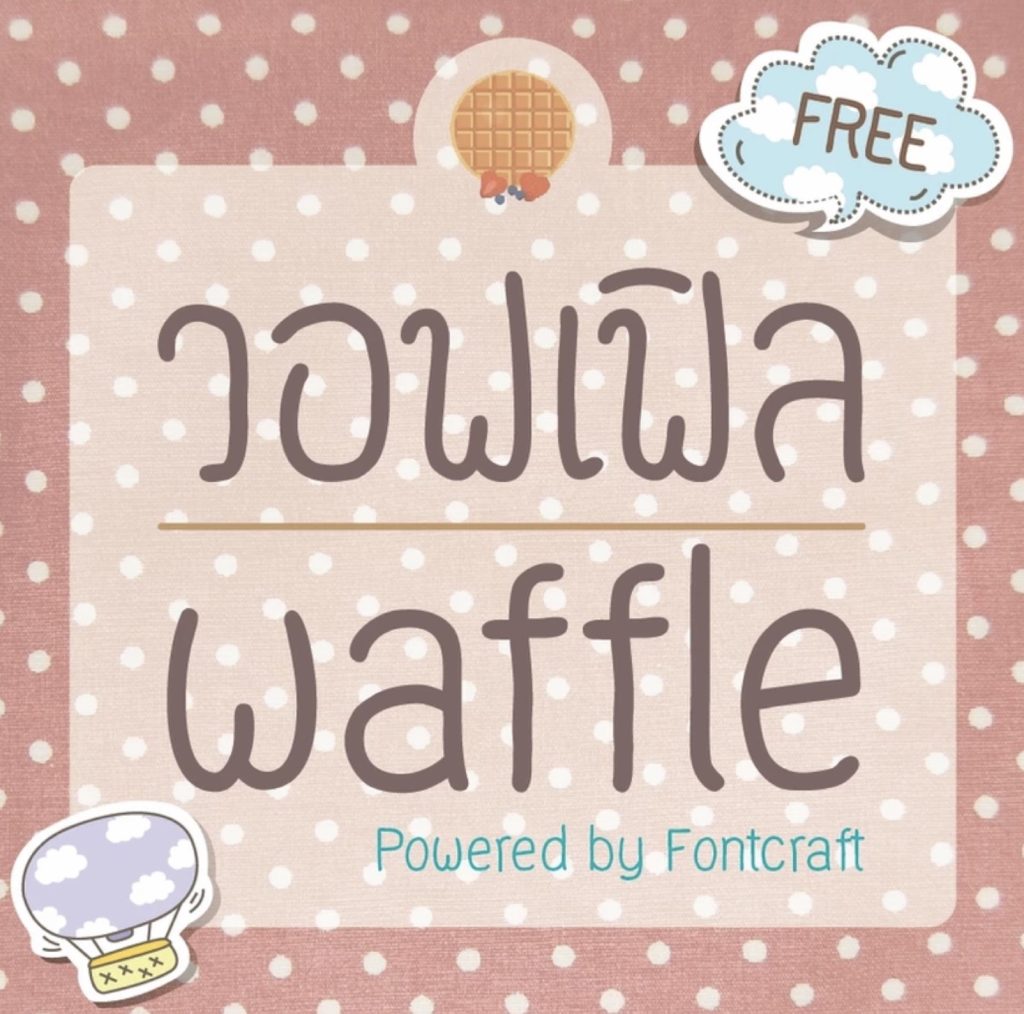
ฟอนต์เป็นส่วนหนึ่งที่ช่วยให้ผลงานนำเสนอหรืออาร์ตเวิร์คนั้นมีความสวยงาม สำหรับใครที่กำลังหาฟอนต์ไทยน่ารัก ๆ ไปตกแต่งผลงานส่วนบุคคล ทีมงานได้รวบรวมฟอนต์จาก Fontcraft หรือเรียกชื่อย่อว่า FC มาแนะนำให้ดาวน์โหลดไปใช้งานกันค่ะ
รวม 8 ฟอนต์ไทย คัดมาแล้วว่าน่ารัก ตกแต่งสวย จาก Fontcraft ดาวน์โหลดฟรี
1. เอฟซี มาร์ชเมลโล่ (FC Marshmallow)
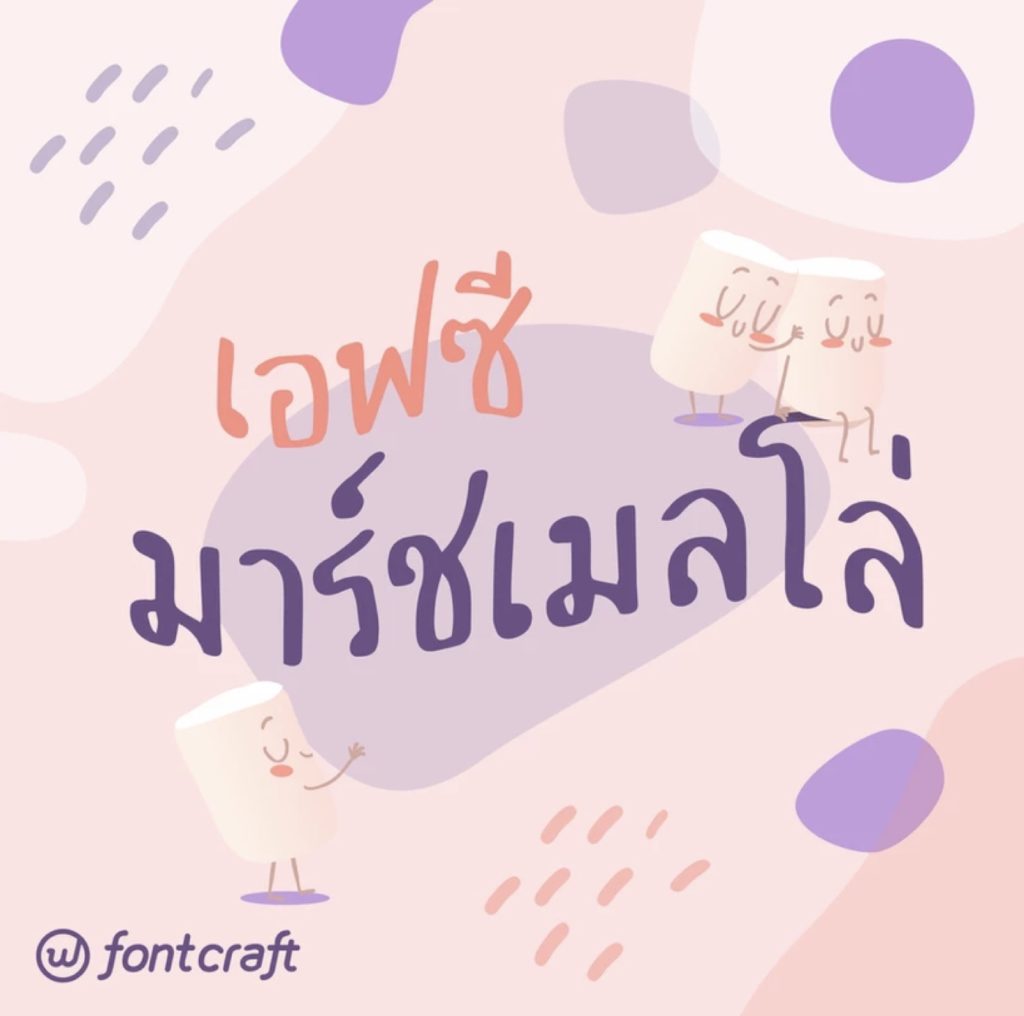
2. เอฟซี มอเตอร์เวย์ (FC Motorway)
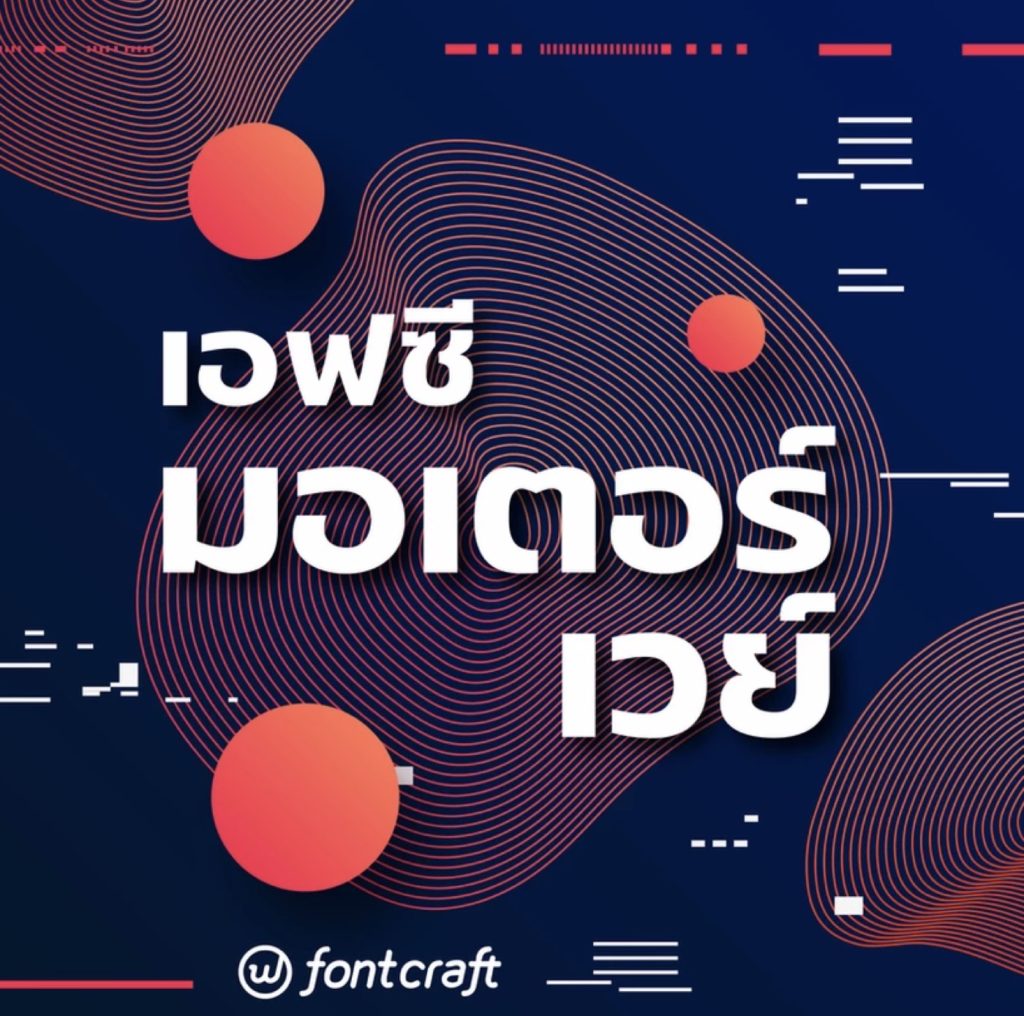
3. เอฟซี มัฟฟิน (FC Muffin)
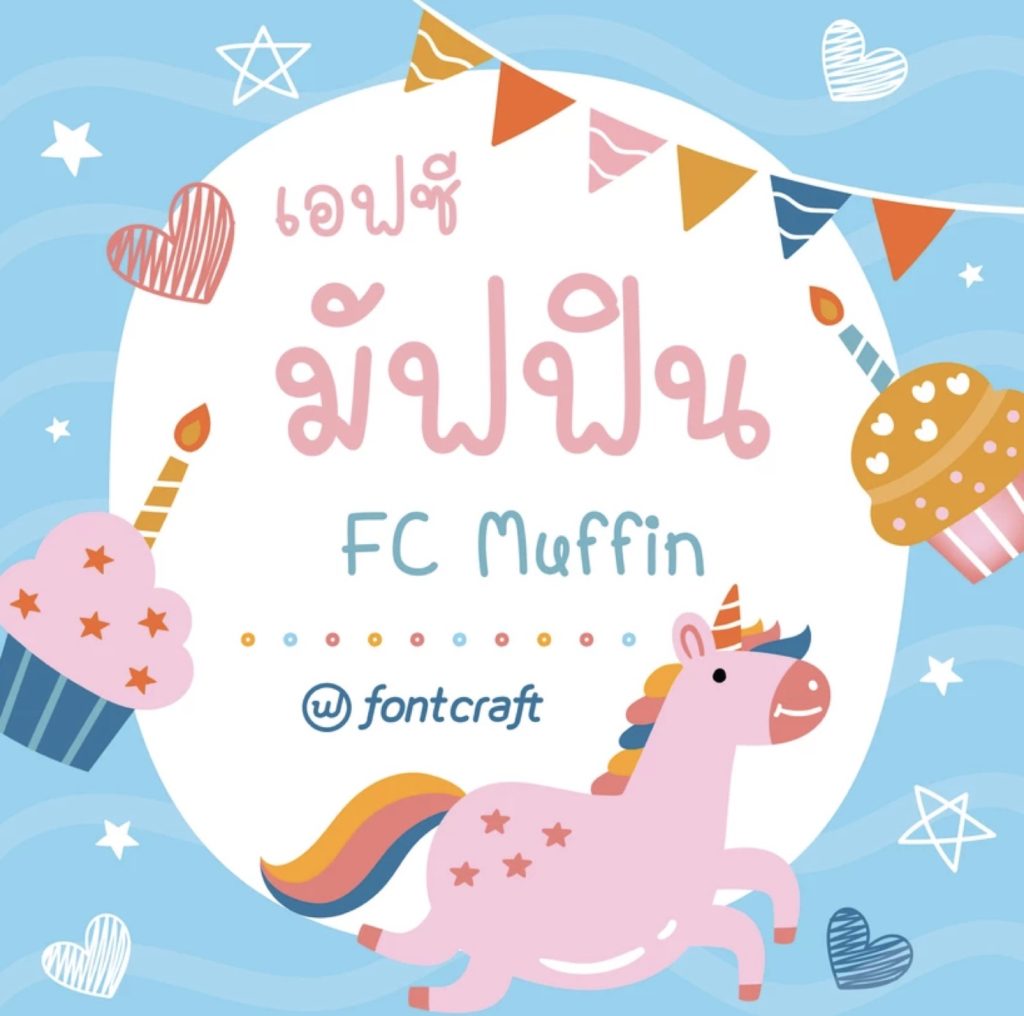
4. เอฟซี โฮม (FC Home)
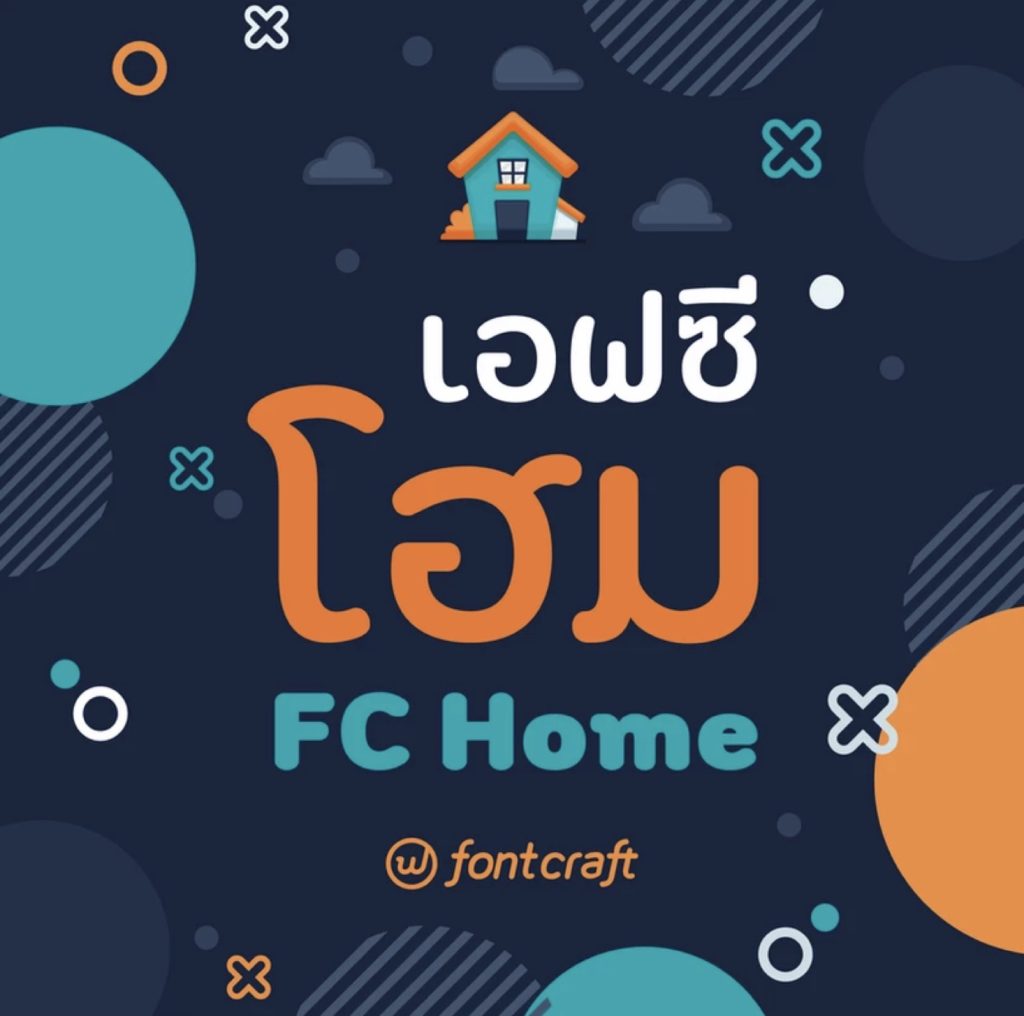
5. เอฟซี เพาะรัก (FC PorRak)
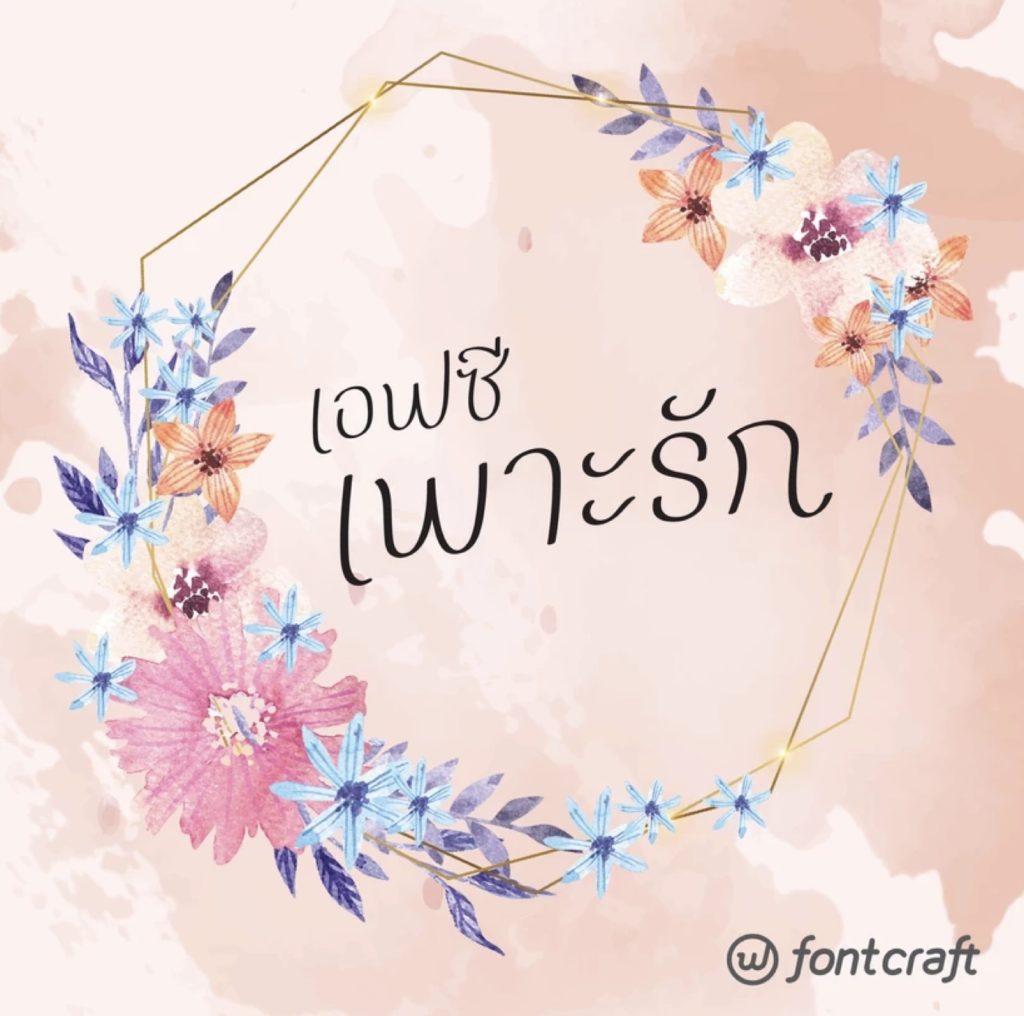
6. เอฟซี ขนมผิง (FC Knomphing)
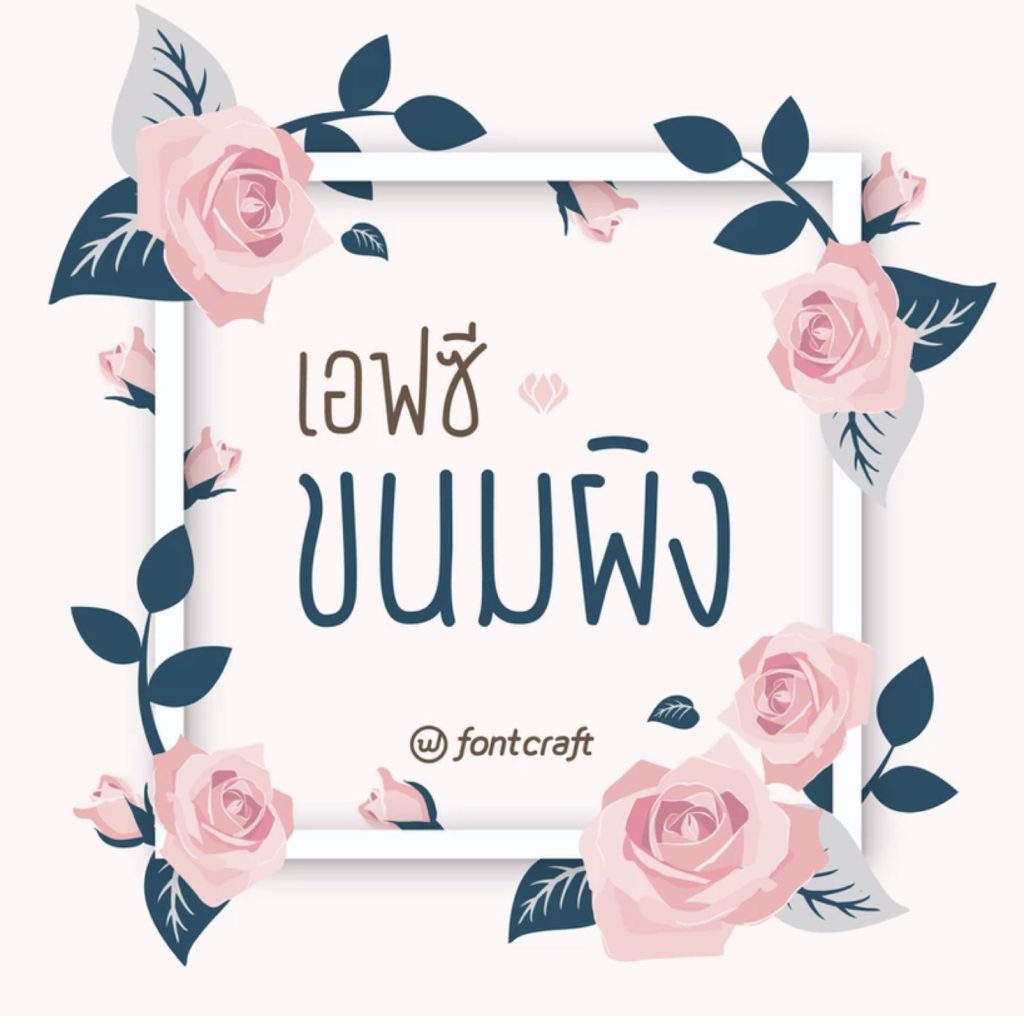
7. เอฟซี ละมุน (FC Lamoon)
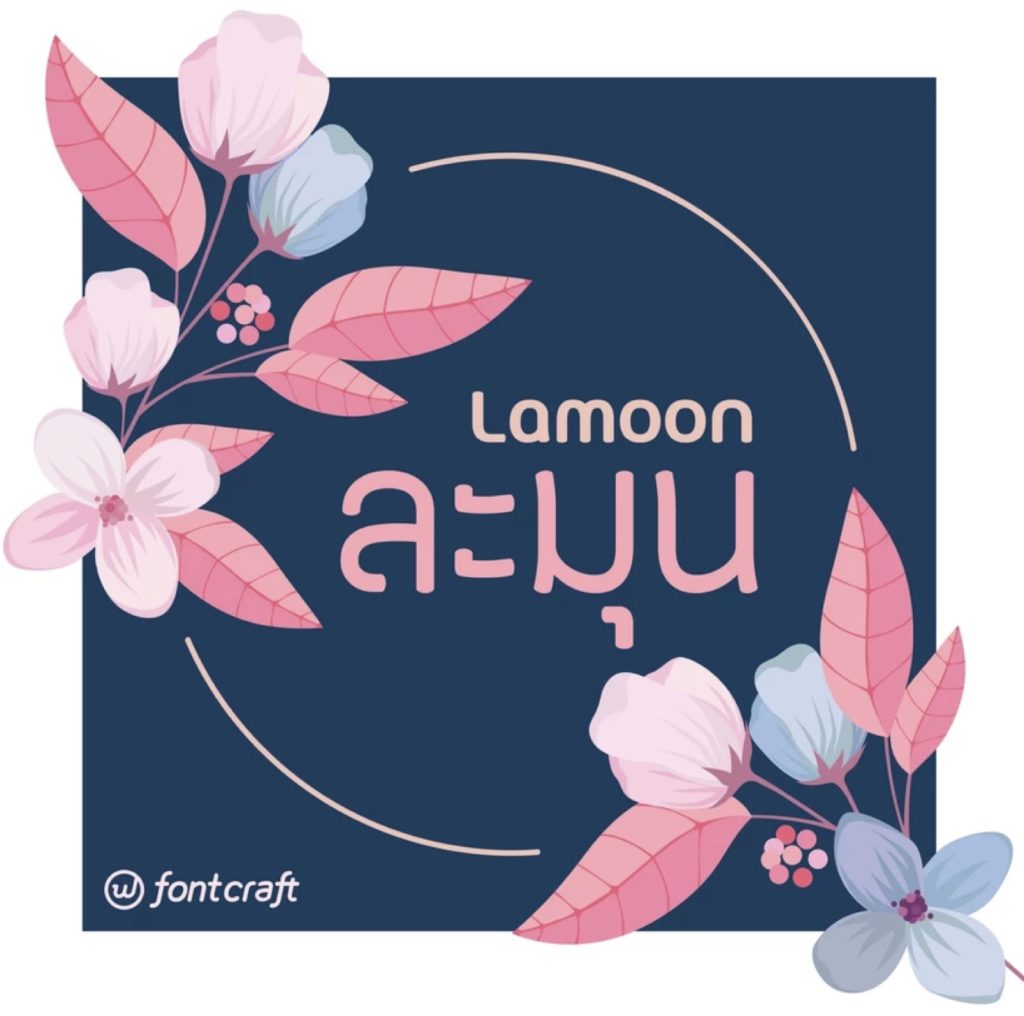
8. เอฟซี วอฟเฟิล (FC Waffle)